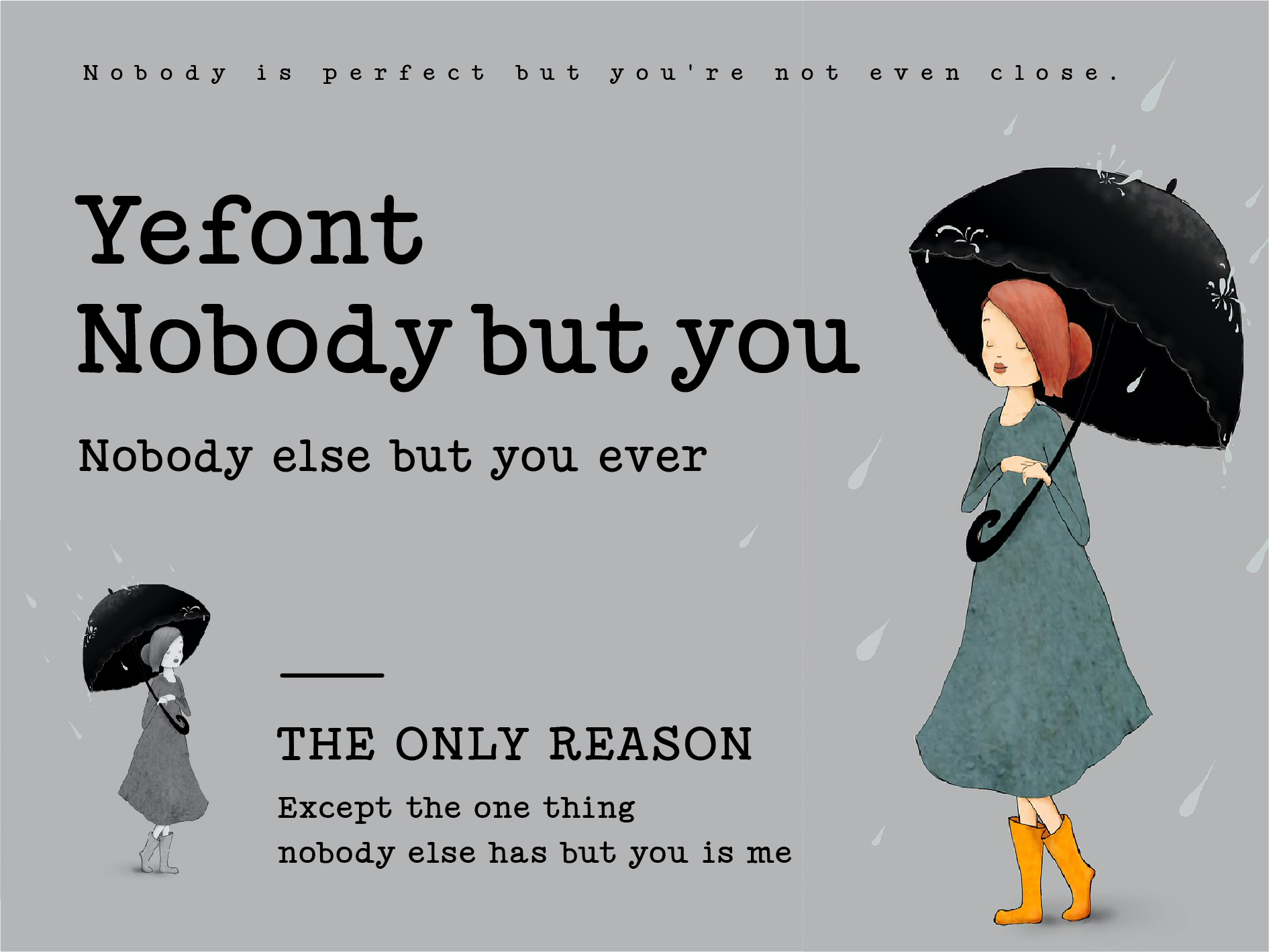
YEFONT Nobody but you
YEFONT Nobody but you,YEFONT Nobody but you是一款纯粹美好的衬线展示字体,这款字体让人想起风趣的插画彩页、色彩浓郁的法式电影镜头、春天公园里的花朵、蓝天白云以及可以躺下的草地等一系列可爱的画面,非常百搭地适用于任何平面设计领域。